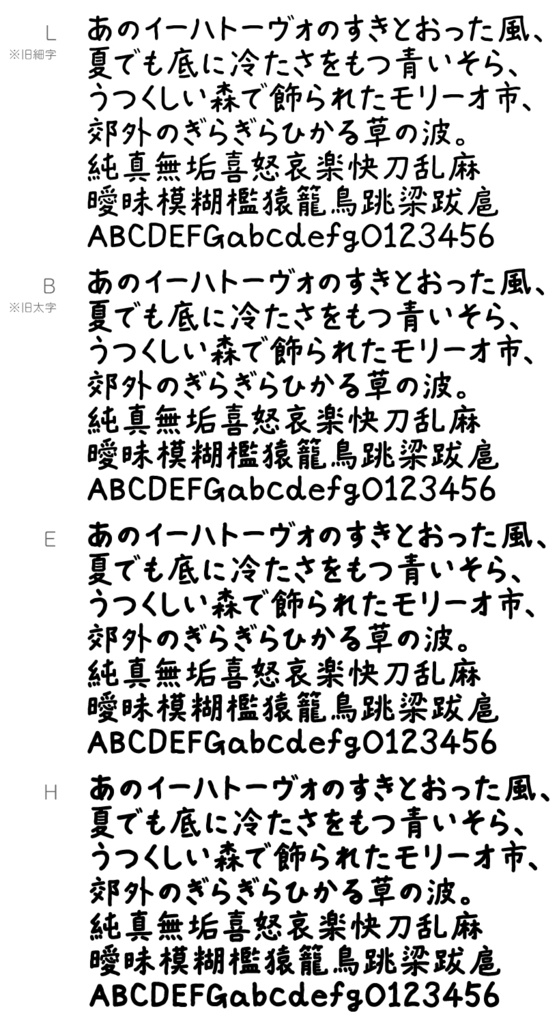
TK-takumi書痙フォントのL・B・E・Hウェイトのセットです。 等幅・プロポーショナルフォントを同梱しております。 ※2019年5月からの新元号「令和」の合字も入力できます(U+32FFに収容)。 ※当フォントは2023年夏にリニューアルし、ウェイトのバリエーションが増えました。 従来の「細字」「太字」と、現在販売している「ウェイトL」「ウェイトB」は同一の太さです。
どんなフォント?
フォント好きで、でもただのユーザーだったtakumiが初めて自分で作りきった完全オリジナルフォントです。 フォントや漢字が大好きで、でも書痙に悩んでいるから整った字が書けないtakumiがその気持ちをフォントにぶつけるために、ペンタブで1文字ずつ書いて作りました。たくさん時間が取れた大学2年の夏より制作を始め、1ヶ月100時間以上(最長1日4時間程度)の時間を取り、同年冬までかけて数千字に渡る収容文字(かな・英数字・記号類・漢字etc)を完成させました。 「takumi書痙フォント」が完成するまでの物語を掲載しています。ぜひ、併せてご覧ください♪ https://slimedaisuki.com/blog-entry-3786.html